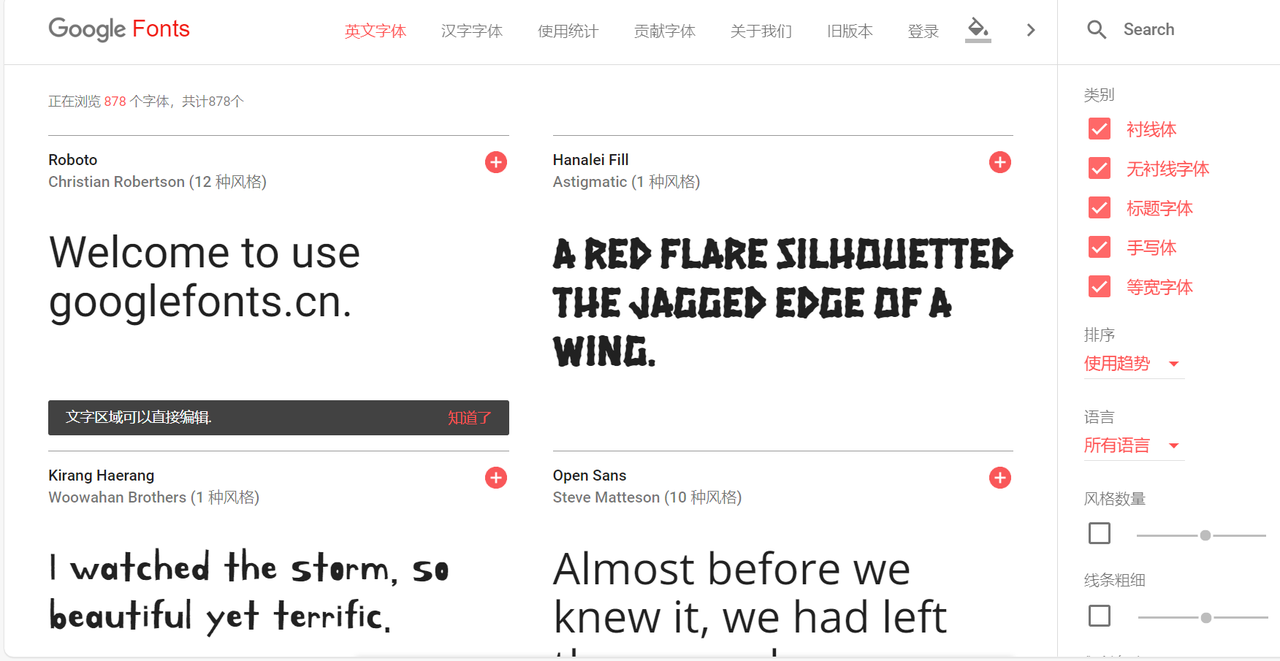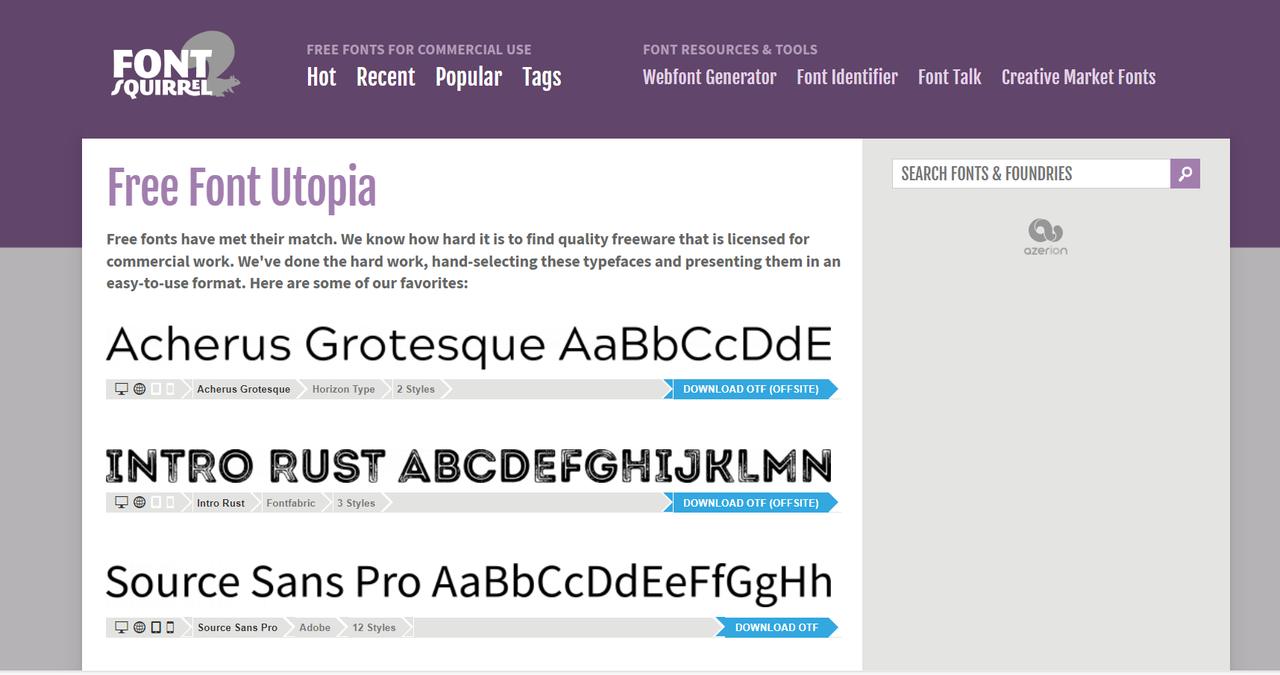
无衬线字体下载网站:永久免费商用,网页 / 海报 / LOGO 适用
无衬线字体是近年来设计师们日常使用频率最高的字体,因为它的笔画简洁利落、风格现代且大气,在网页 UI 设计、品牌 logo 设计、商务 PPT 设计等领域被广泛应用。然而,市面上的商业字体授权复杂,一不小心就容易陷进版权纠纷。为此,本文特地给大家整理了一系列优质的无衬线字体下载网站,所有网站都提供免费商用的无衬线字体哦,网页 / 海报 / LOGO 全都适用。从国内备受好评的一站式字体管理神奇到国外专业级的免费字体资源库,每个网站都各具特色,近期正在发愁找不到合适的商用字体的小伙伴们赶紧码住这些网站,帮助你快速找到心仪的无衬线字体。
一、字由
作为一款集字体资源、AI工具、字体管理于一体的综合性平台,字由不仅是一个简单的无衬线字体下载网站,更是一个专业的字体管理神器。截至目前,字由官网已经收录了上万款字体,其中免费商用字体高达3590款,资源量非常之高。最关键的是,这些字体均有第三方厂商的正版授权,耳熟能详的字库你都可以在这里找到清晰标注授权类型的字体资源。关于无衬线字体下载,它提供了阿里巴巴普惠体、思源黑体、字由文艺黑、优设标题黑等一系列热门选择,无衬线英文字体同样有很多,可以说日常设计需要的大部分字体,这里都能找到。
另外,如果你经常要管理大量字体,字由的客户端还支持在 PS、AI、ID、XD、Figma、Sketch、CDR 等设计软件中一键应用字体,无需下载安装字体包,即可完成字体应用,省去了字体查找,下载,安装的麻烦,效率大大提升。
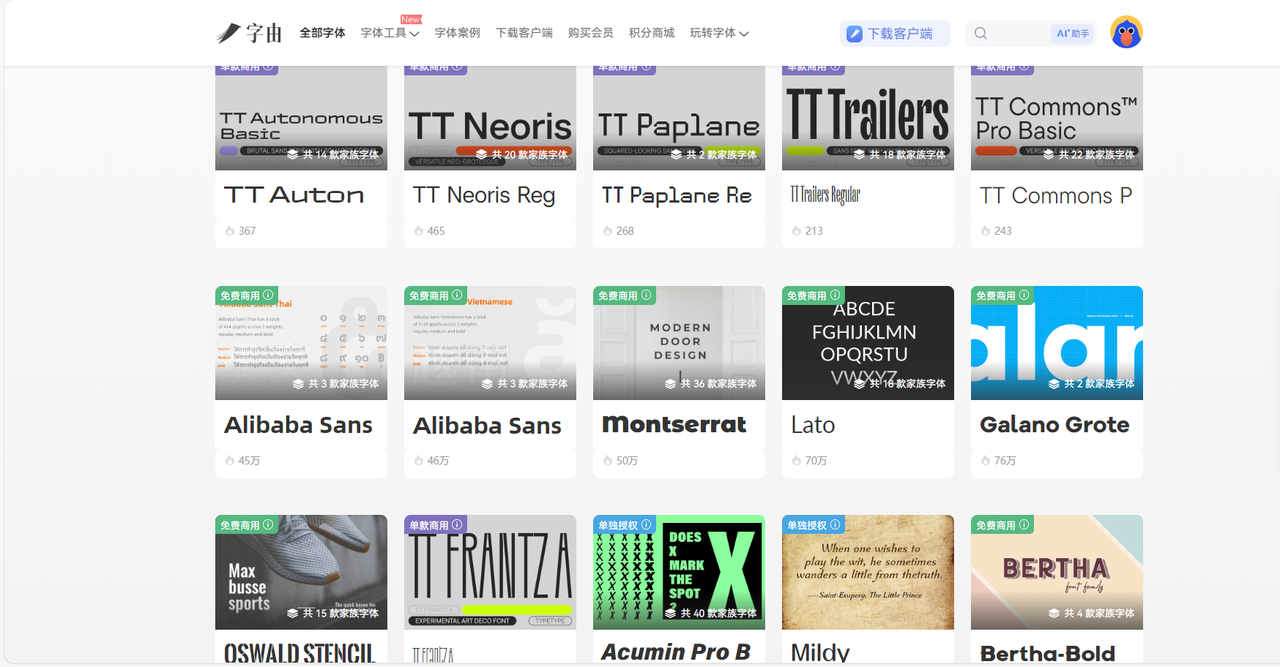
二、Google Fonts
Google Fonts 是由谷歌运营的全球最大的免费开源字体库,所有自已都以开源授权方式面向用户开放。该网站主要覆盖了衬线、无衬线、标题、手写、等宽 5 种字体类型,而且无论你使用的是 Windows、macOS 还是 Linux 系统,下载安装都非常方便。我认为 Google Fonts 最大的亮点就是筛选功能,你可以在右侧工具栏按照字宽、倾斜角度、线条粗细、风格数量、语言、字体类别等特征来精确定位自己想要的无衬线字体样式。进入每个字体的详情页之后,你还可以直观看到不同字符(字母、拼音、标点符号等)的呈现效果,让你对这款字体的了解更深。
由于 Google Fonts 是面向全球设计师开放的网站,所以字体语言选择非常多,例如孟加拉语、希腊语、法语、韩语等等,如果你经常要做一些国际化项目的设计,它绝对是一个下载字体的绝佳平台。
三、Font Squirrel
Font Squirre 始终专注于提供商用免费字体,该网站内的每款字体都是经过人工严格筛选后上传的,绝对可以保障版权的合规性。Font Squirrel 拥有精细的分类系统,你可以按照风格、特征、应用场景等多种维度寻找字体资源。它还提供了字体识别工具,你如果遇到一款好看但不知道名字的字体,可以上传图片来识别,它还会给你推荐类似的免费字体哦。值得一提的是,Font Squirrel 专门为响应式网页设计设置了一个单独的“Webfont”版块,可以优化字体文件的加载速度和字体呈现效果,有需要的小伙伴不妨来尝试一下。
四、Befonts
日常追求美学设计的小伙伴可千万不要错过 Befonts,它主打精美的无衬线字体下载,整体风格现代简约,非常符合当代设计师的审美,力求给大家提供视觉创意极佳的字体资源。这里的无衬线字体资源尤为丰富,从简约的集合无衬线体到柔和的手写感无衬线体,再到科技感满满的未来风字体,更重要的是每款字体都附带了详细的设计师说明,让你快速了解字体的设计理念,便于你找到适配自己设计风格的字体。比起用它下载字体,我经常会把 Befonts 当成一个不错的灵感来源,因为这里的字体简约且富有设计感,会根据潮流趋势定时更新字体,能培养一些独特的审美价值。
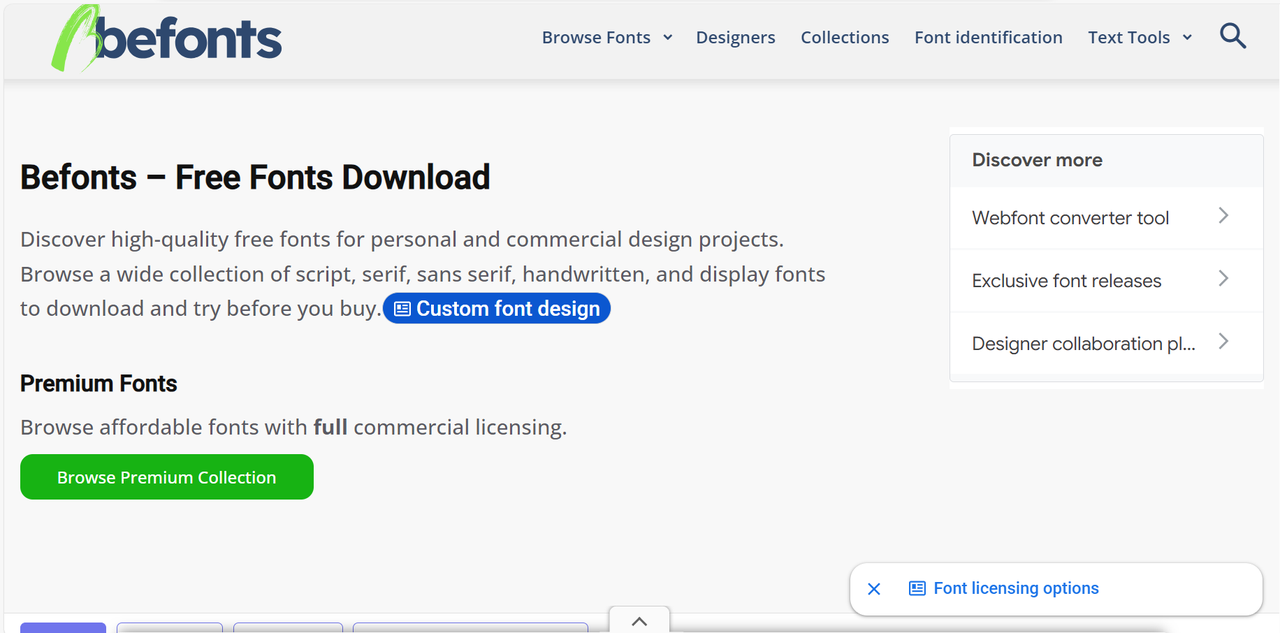
五、DaFont
DaFont 是一个汇集了全球设计师作品的大型老牌字体社区,它经典的红白界面相信很多资深设计师都非常熟悉。从设计应用的角度来看,DaFont 中的无衬线字体非常适合用于文创周边、海报标题、国潮设计等需要个性表达的场景,这些字体往往都在保留清晰易读的同时,又加入了设计师的独特审美,显得每个字体都更加有辨识度。这个网站可以说是我见过的字体分类最细致的 ,想要下载无衬线字体就点击“Basic”分类下的“Sans serif”,只要输入文字内容就可以在线预览字体效果,非常方便。
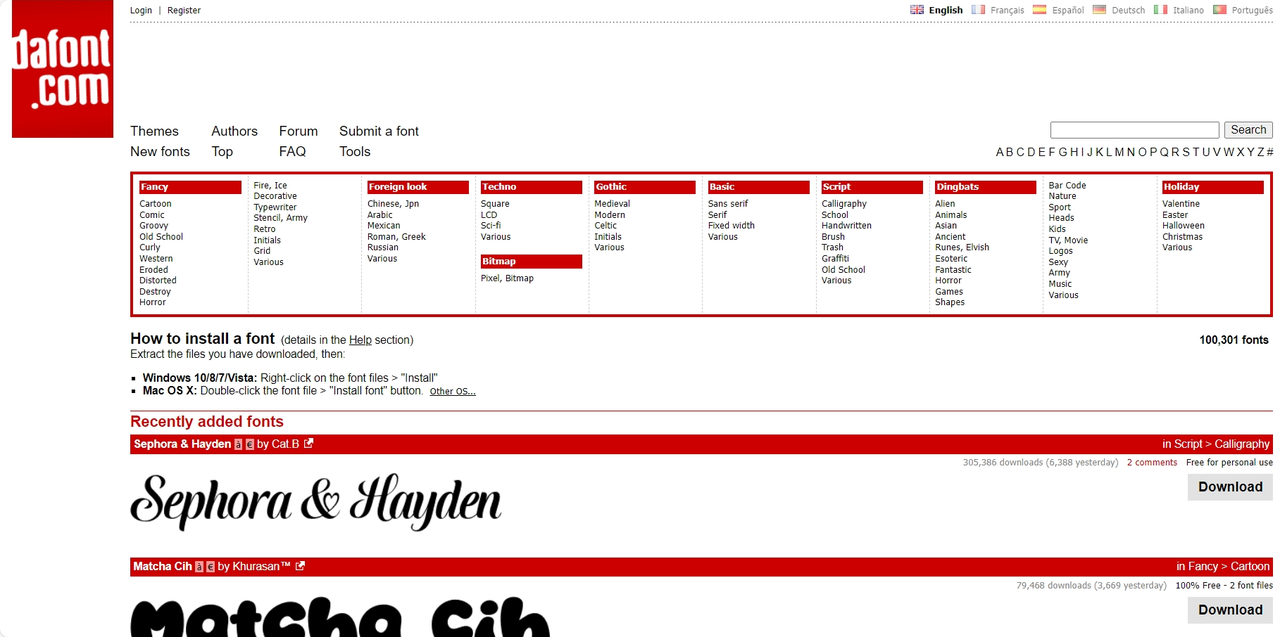
以上就是本次为大家整理的无衬线字体下载网站合集,每个网站都以独特的方式为大家提供了丰富且可靠的无衬线字体资源。无论你正处于哪种设计行业,或者是自媒体创作者,都乐意根据自己的需求找到最适合的那一个网站。就我个人体验来讲,还是更推荐字由,字体模板多到数不清,版权标注也清晰明了,全中文页面极度适配我们的使用体验。话不多说,大家自己上手体验一下吧,让这些无衬线字体为你的设计作品注入全新的视觉活力!